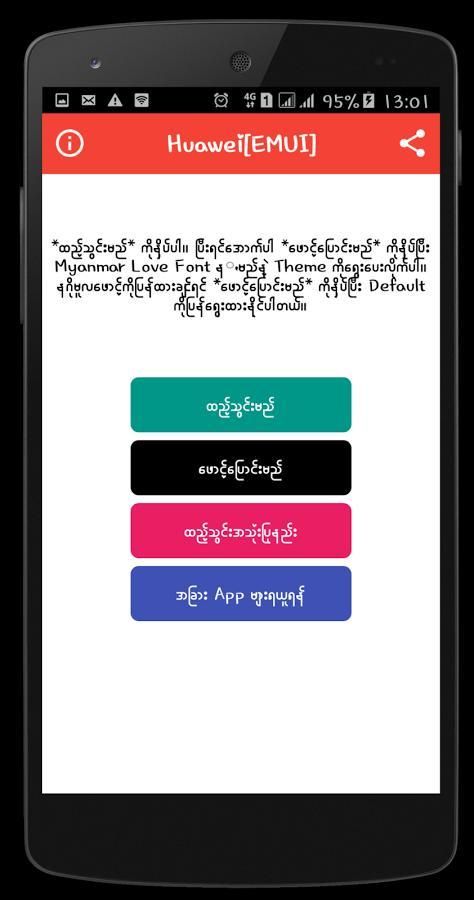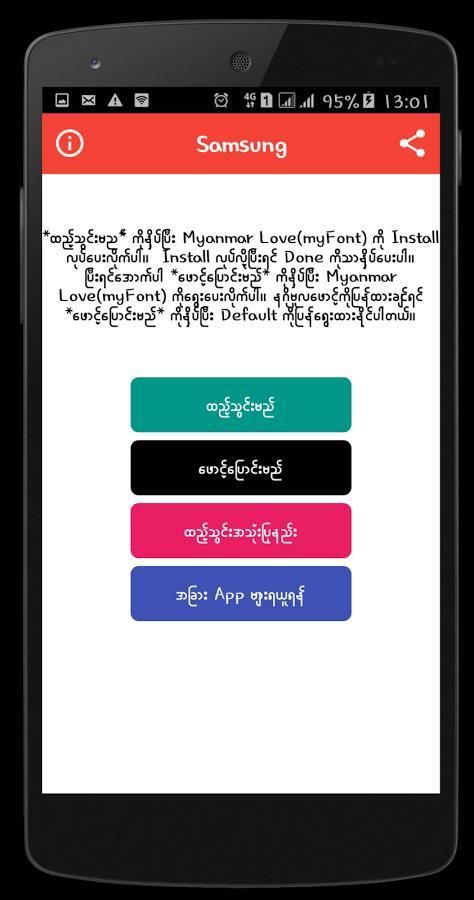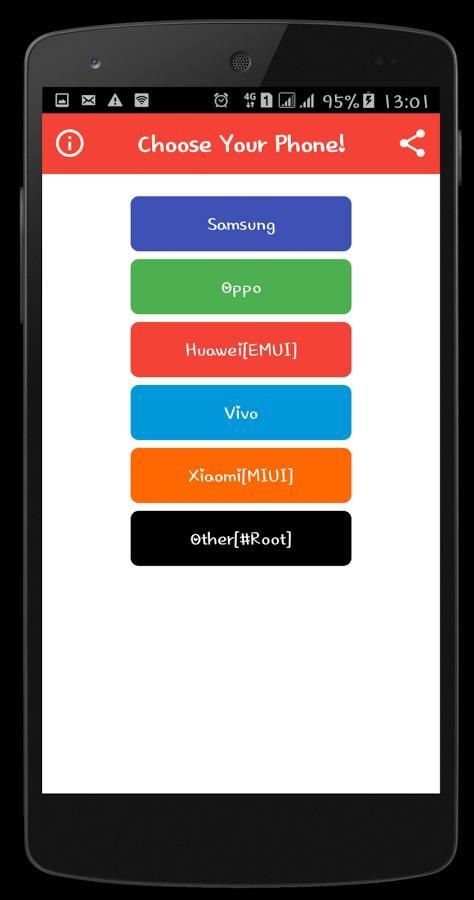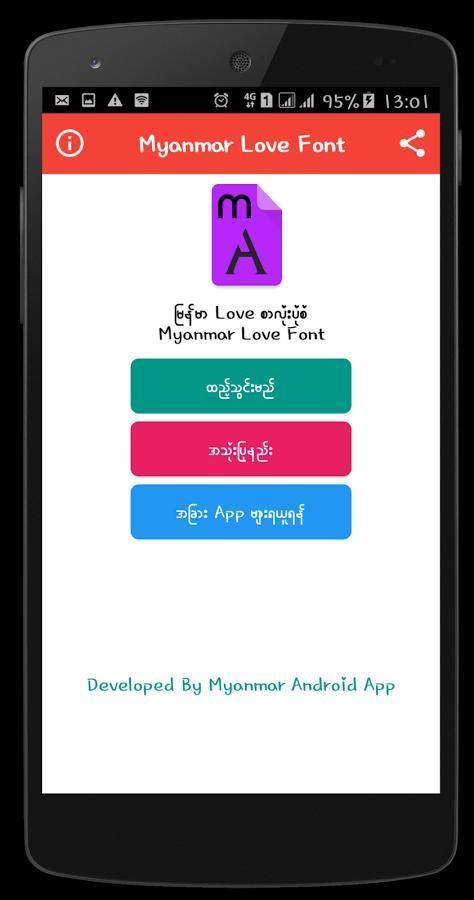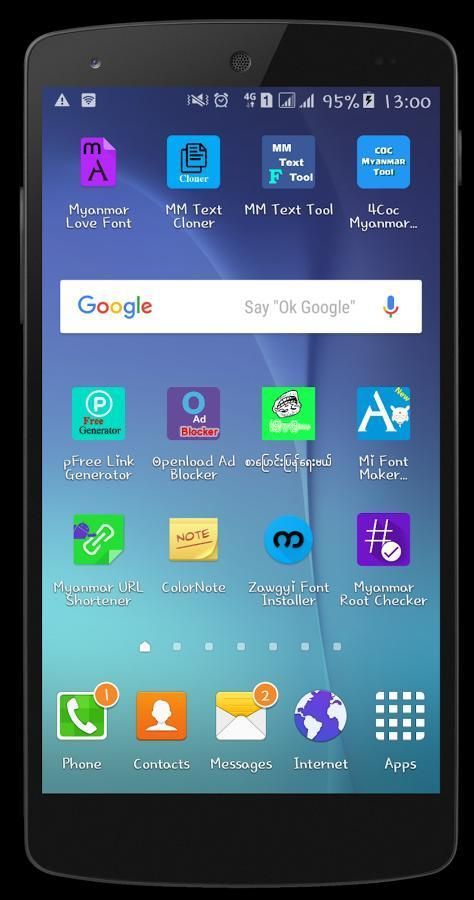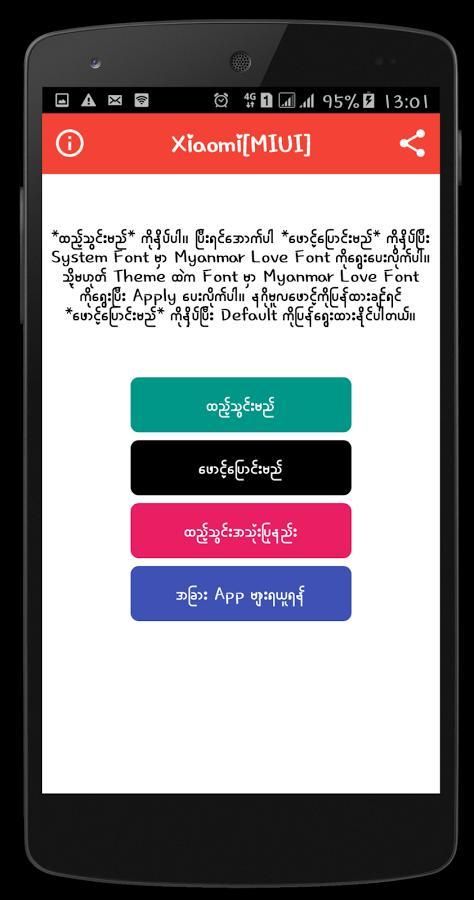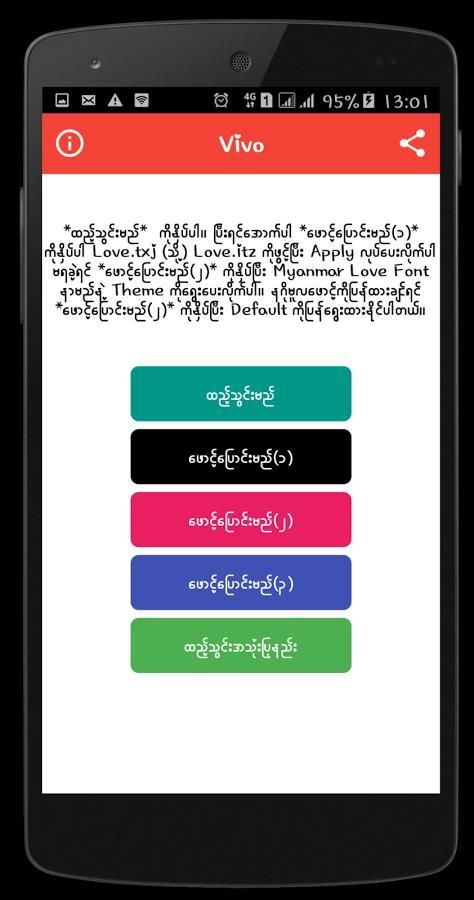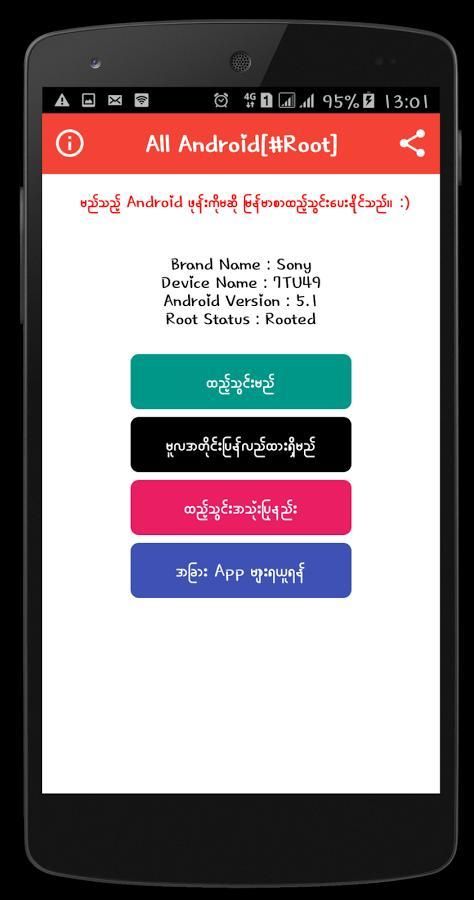
"Myanmar Cinta Font" Root မ လို ထ ည့ ္ သြင္း ျ မန္ မာ စာလုံး အလွ တစ္ ခု ျ ဖစ္ ပါ သည္.
ဖုန္း မွာ ျ မန္ မာ စာလုံး အလွ သုံး ခ် င ္ သူမ် ား အ တြက္
Myanmar Cinta ဆိုတဲ့ စာလုံး အ လန္း ေလး တစ္ ခု ပါ.
အ ရမ္း လန္း ပါ တဲ့ စာလုံး ပုံ စံေ လး ပါ.